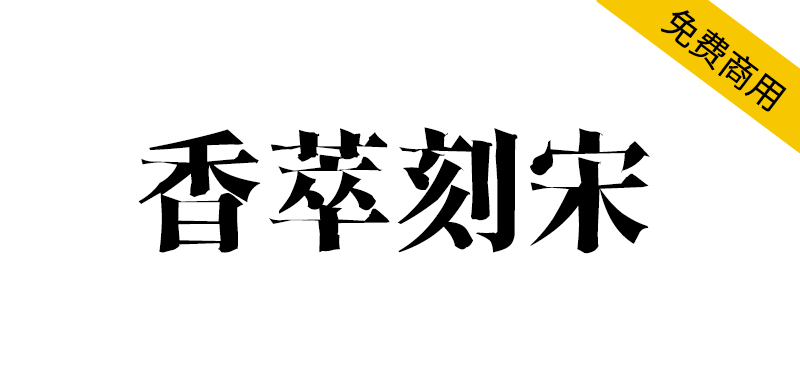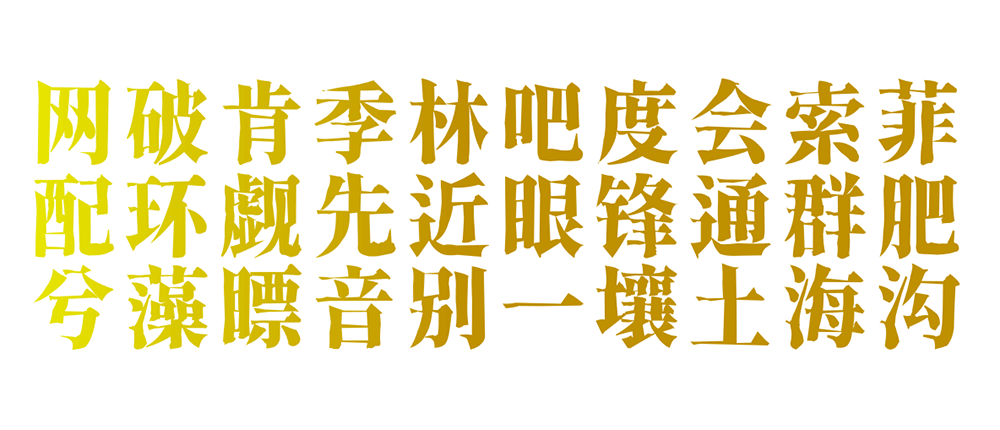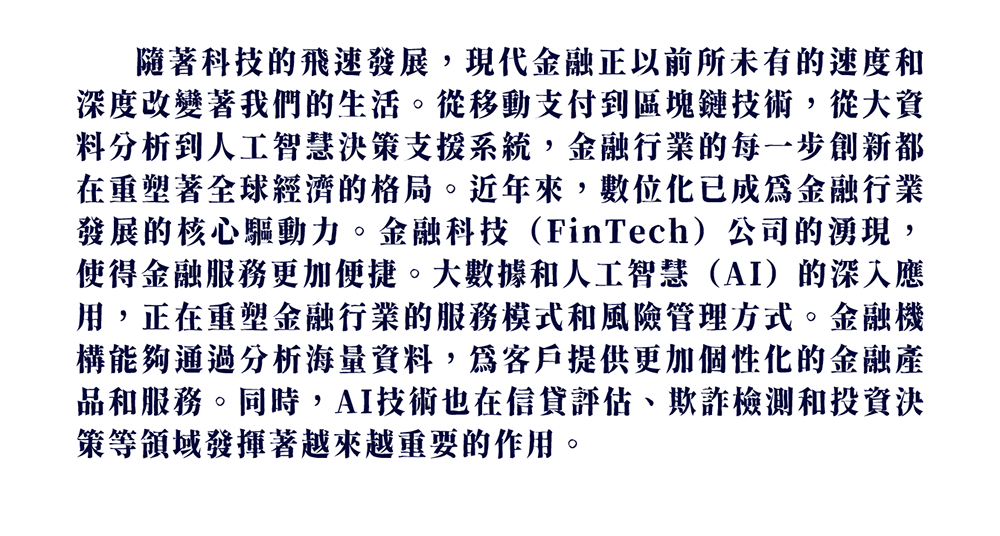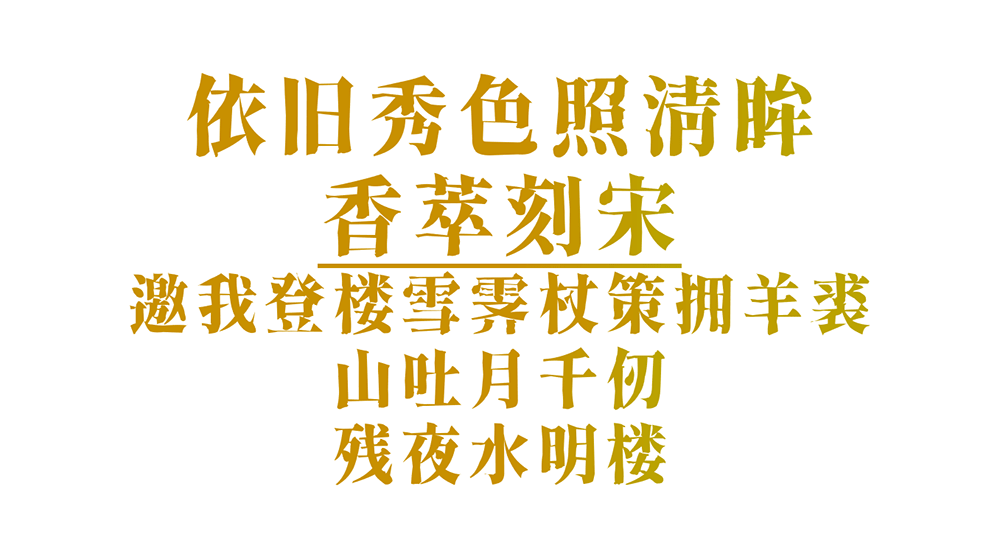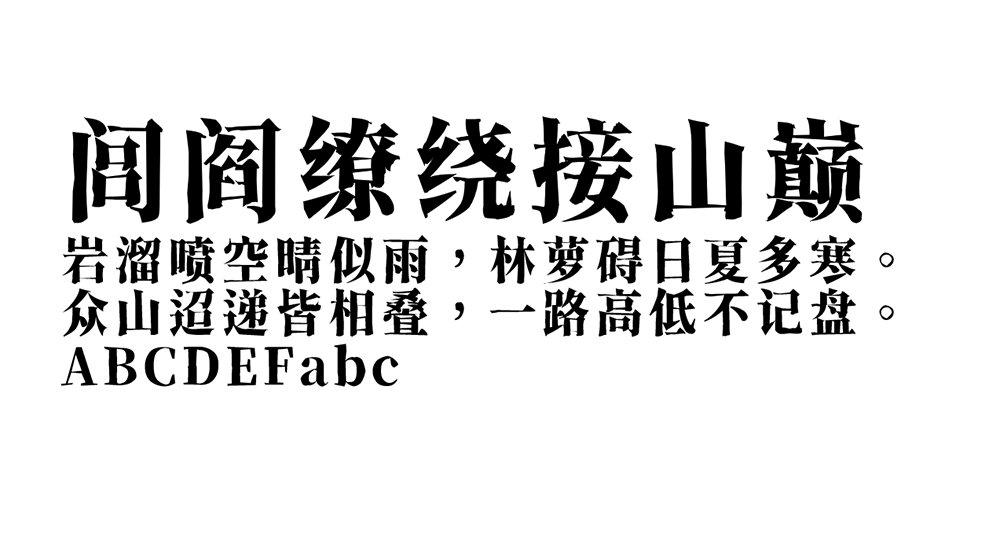
“香萃刻宋”(Xiangcui Kesong)是一款基于思源系列开源字体改造而成的中文字体,支持简繁汉字,允许个人或企业免费商用。“香萃扁刻宋”(Xiangcui Bian Kesong)为其衍生作品。
这款字体有意模仿了雕刻宋体的外观特点,通过仿古的处理,达到兼具端庄和典雅的特征。字体笔画尖锐,特色明显,视觉吸引力强,适合各类设计与印刷,有浓烈的视觉增强效果。字体普遍使用旧字形,同时适用于标题和正文。用作标题时,笔画的粗糙感强,特点明显,富有文学感与人文气息。